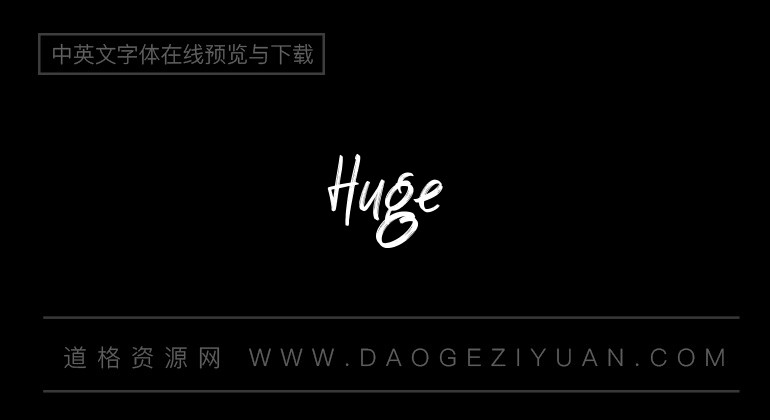
Huge 字体是一种多功能的字体,它可以用于多种设计项目,从简单的文字设计到复杂的排版。它的特点是字体粗细可调,字形精细,字符间距紧凑,可以提供更多的灵活性。它可以用于网页设计、印刷品设计、图形设计等多种应用场景。内容介绍
Huge是一款非常不错的手写艺术字体,具有很好的视觉感,适合于文化类的宣传设计、商业类品牌的广告和产品包装设计以及个性化文字排版等较多场景。